一、字体设计的原则,我们要注意以下几点:
1. 易辨识性。(清晰的视觉印象)
2. 独特性(设计主题、突出汉字设计的个性色彩)创造与众不同的独具特色的字体。形态特征与组合上进行探求,拓展方块字扩展方法。人们即熟悉又陌生的视域中获得新的表现(视觉冲击)
3. 审美性,真善于内,必美于外。(需要注意使用场合、对象、范围、汉字所要表达的意义及发挥的作用,围绕主题风格特征协调)
字体设计成功与否。不仅在于自身的书写。同时也在于其运用的排列组合是否得当。仅是形状与线条等的随意组合。缺乏视线流动感,不仅会影响汉字体本身的美感,也不利于有效的阅读,不但没有“生命”感,而且根本无法视线视觉设计的传达功能。要取得良好的排列效果,关键在于遵循视觉规律。找出不同字体的内在联系,对其不同的对立因素予以和谐的组合,在保持其各自的个性特征的同时,组织成一个具有协调感的有机整体为了造成生动对比的视觉效果:1.风格 2.大小 3.方向 4.明暗度 等方面选择协调相同的因素将对比与协调的因素在表达主题的需要下有效地运用、能造成既对比又协调的。具有视觉审美价值的文字组合。
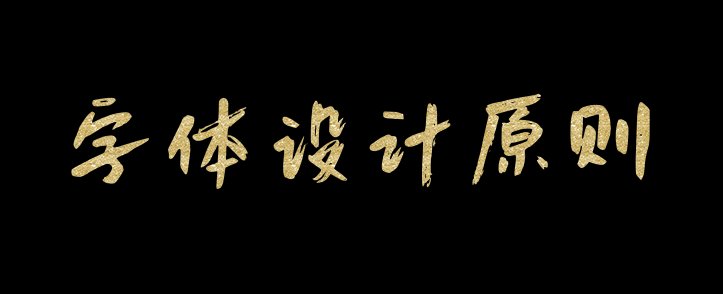
二、字体设计在组合需要注意三点:
1. 视觉流程、理想的视觉流程。①方向 ②顺序 符合人们的认识思维发展的逻辑顺序。自然、合理、富于创意的表达。(汉字于西方文字的区别在于它具有竖排的组合)
2. 文字赋予审美情感,诱导人们的阅读兴趣,因此方式上需要顺应人们的心理感受的顺序
⑴水平方向阅读 左—右 ⑵垂直方向阅读 上—下 ⑶小于45度时 下向上流动 ⑷大于45度 上向下
粗字体:稳定、安全、强劲;细字体:优雅、柔和、细腻、高贵;不规则:活跃,字形富有趣味
3. 视觉空间的布局,汉字笔画所占据的空间与其相对应空白共同构成字的空间,即实空间与虚空间。两者互为背景,互相影响,在汉字组合中,注意虚空间的运用,即字间距及其周围的空白区域。虚空间的运用是否得当直接关系汉字组合好坏。(如字的行距应大于字距,否则观者的视线难以按一定的方向顺序阅读)汉字的造型布局:疏可走马,密不透风。